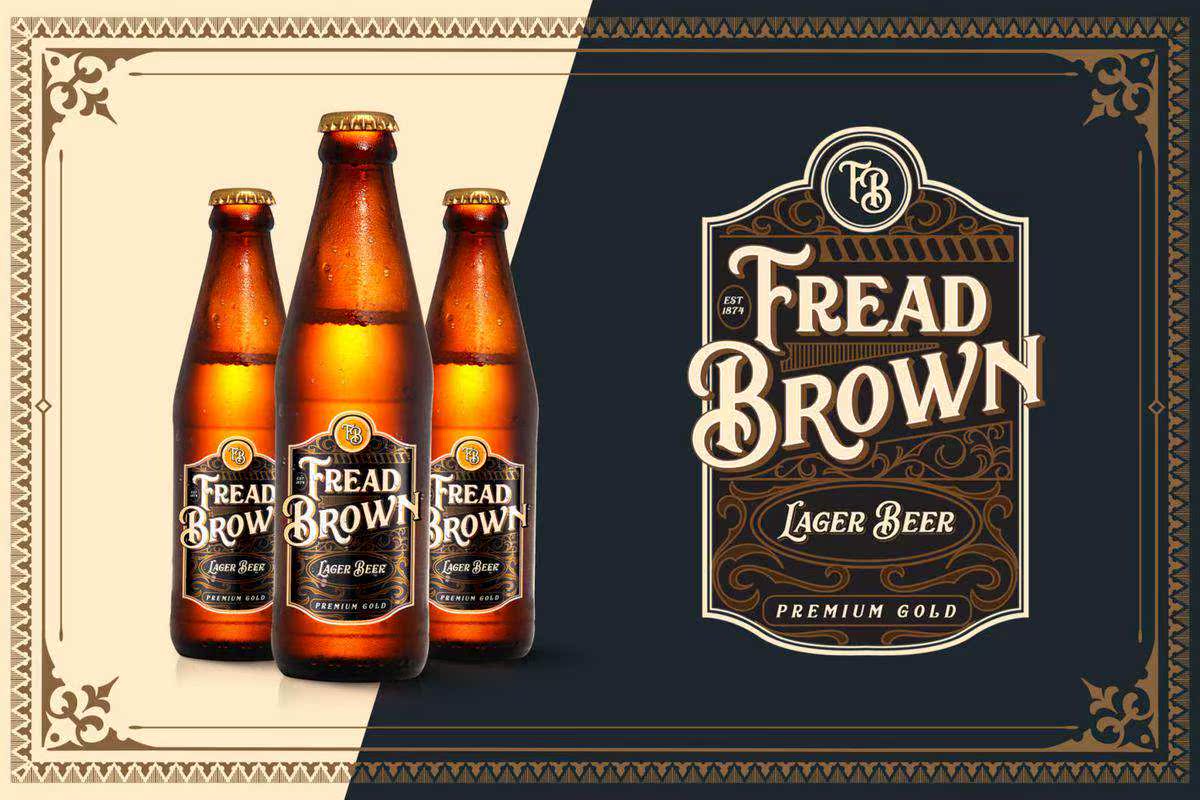
Sacred Bridge是一种非灰白色字体,具有干净和凸版风格,通常和不带装饰和符号。Sacred Bridge适用于品牌、徽章、广告、t恤等各种展示目的。Sacred Bridge是一种非灰白色字体,具有干净和凸版风格,具有额外装饰和符号的常规和传统。神圣的桥梁适用于各种展示目的,包括品牌、徽章、广告、t恤等。